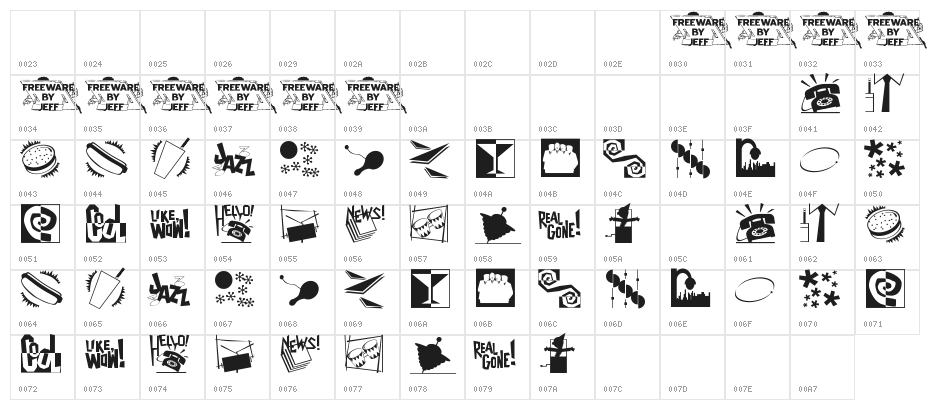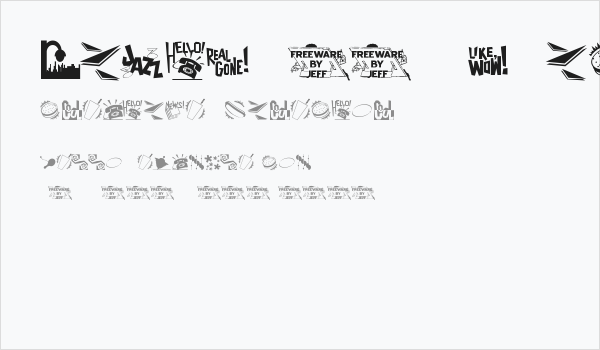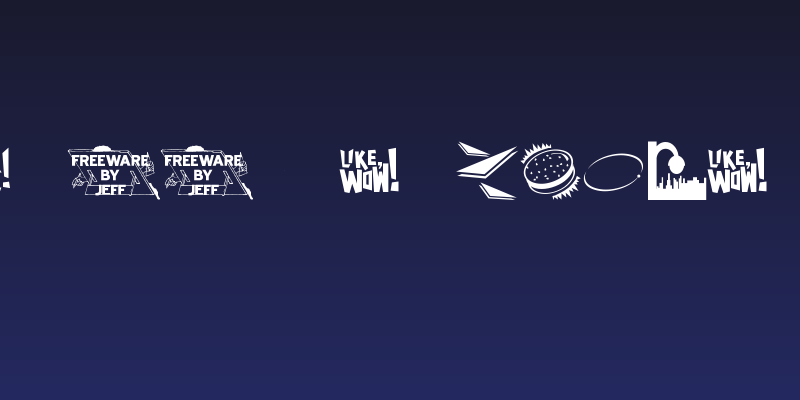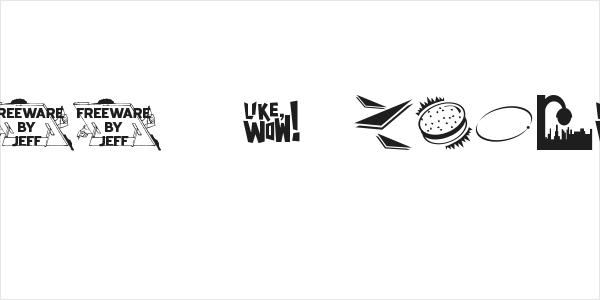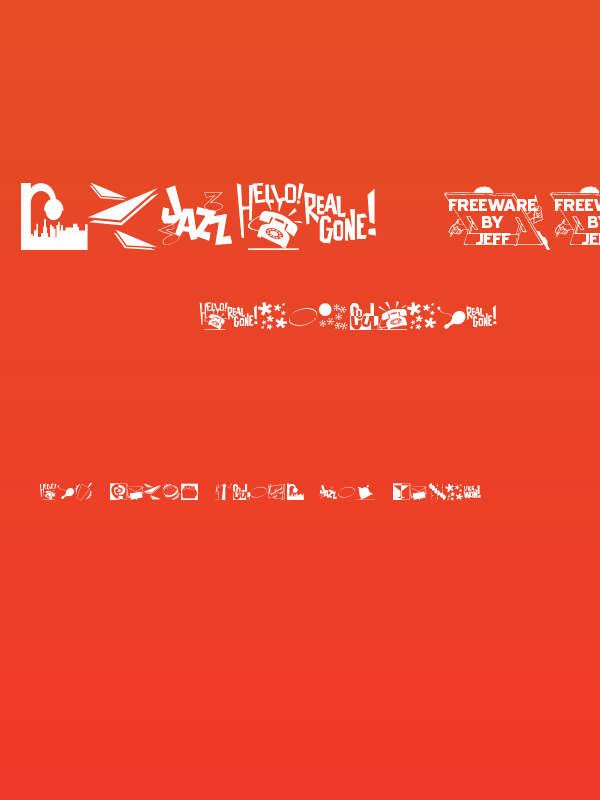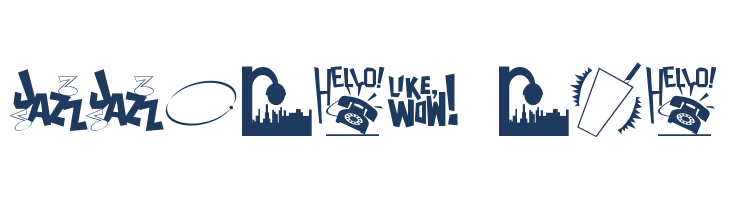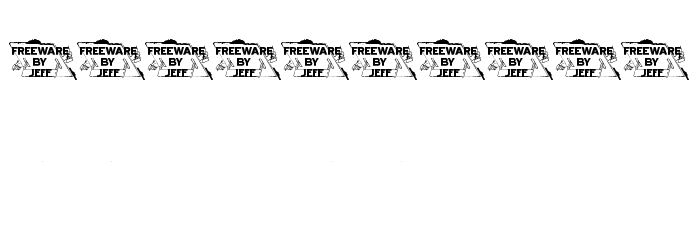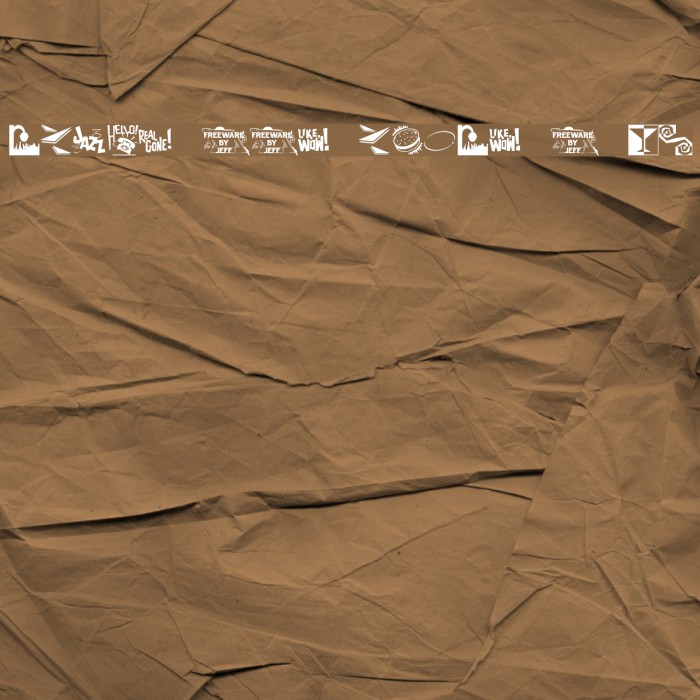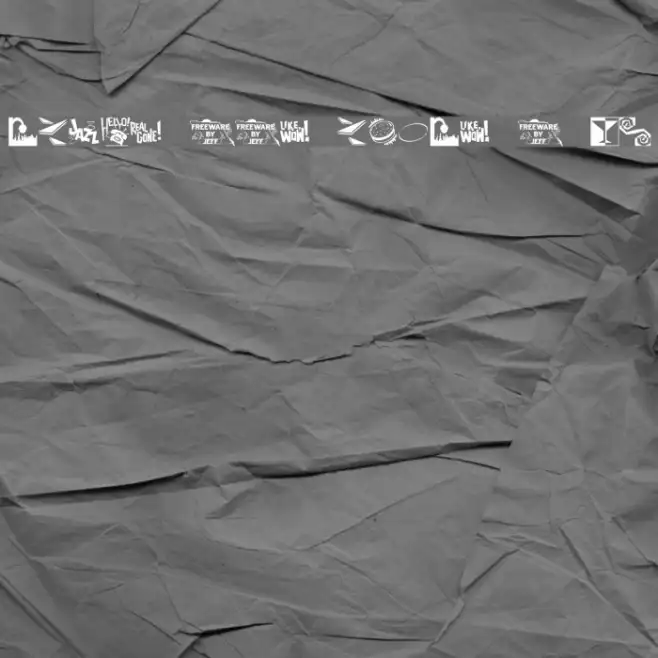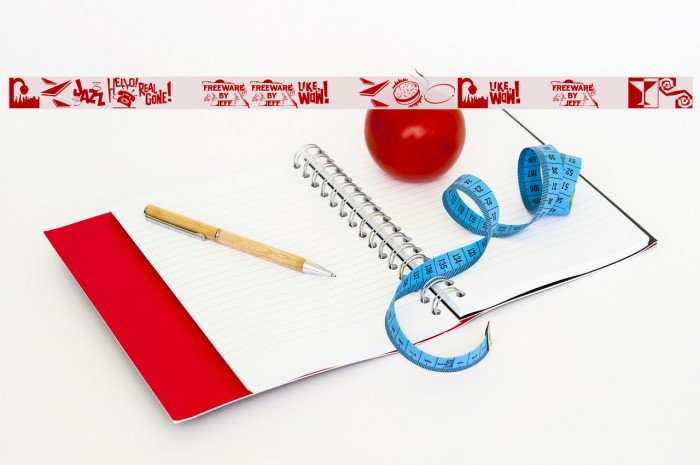
Nifty 50's Icons 2 JL Font
| Caso d'uso | Logos, Decorative elements, Themed events |
| Progetti proposti | Ideal for vintage-themed posters, retro branding, party invitations, and nostalgic web design. |